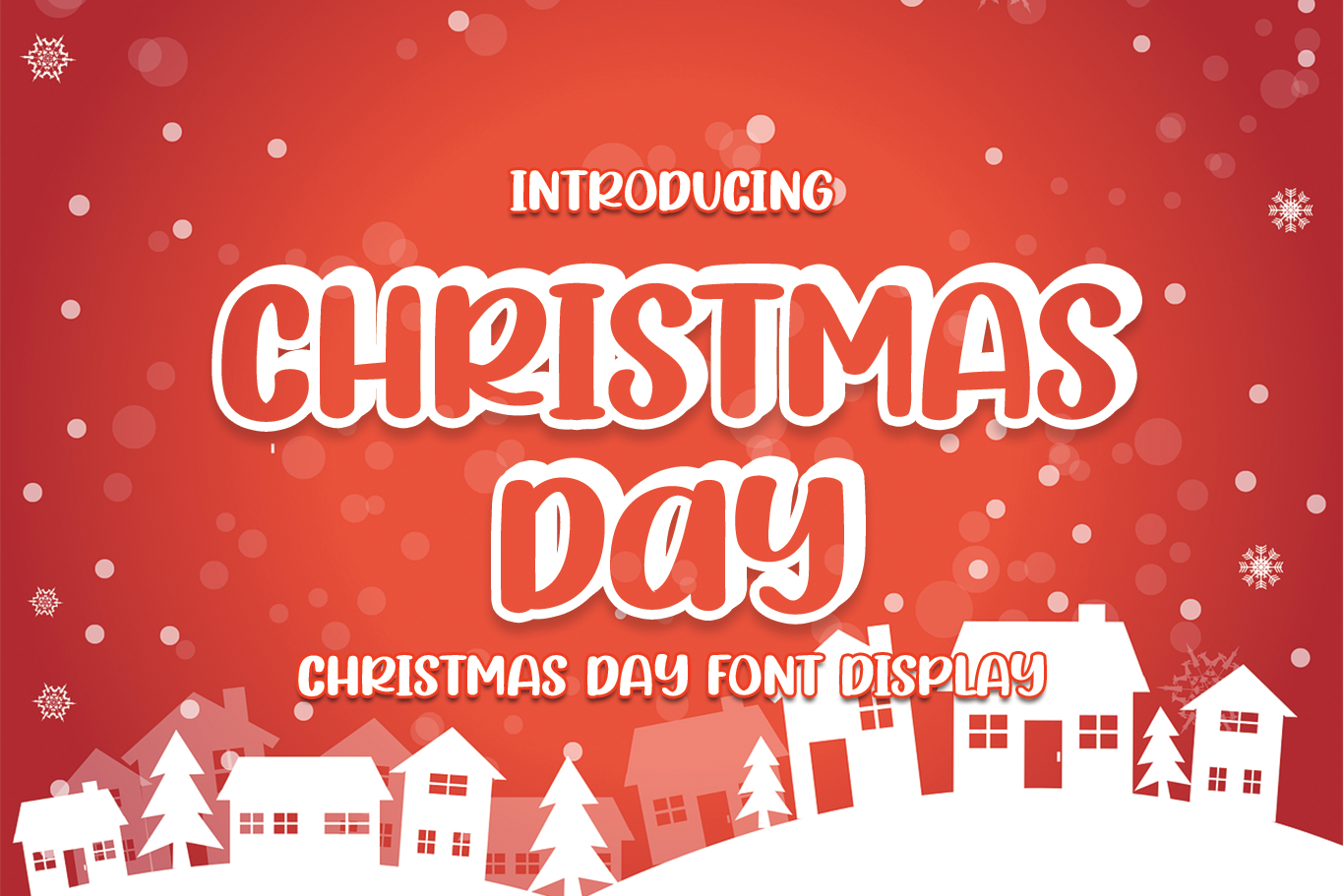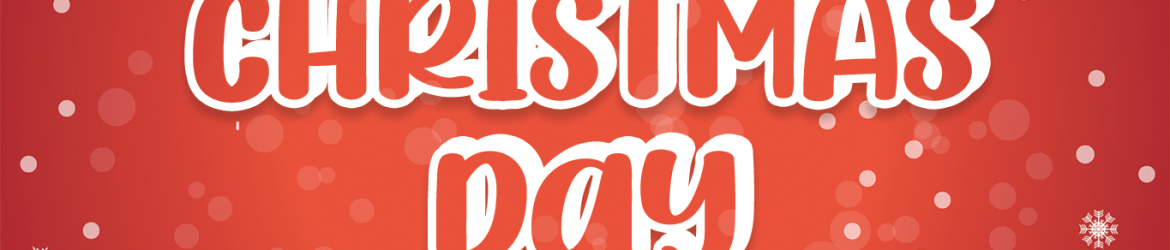
Christmas Day Font – Download Grátis
Esta é uma fantástica fonte de exibição para uso nos mais diversos projetos. Ela tem um ar descontraído e divertido que certamente trará vida ao seu design. Suas linhas retas e seus traços acentuados tornam a Christmas Day Font perfeita para ambientes onde você deseja destacar o texto, seja em cartões de aniversário, calendários ou até mesmo em tatuagens, sem falar dos famosos arquivos de emails de fim de ano. O designer Erik Studio criou uma fonte versátil e original que combina perfeitamente com sua personalidade criativa, tornando seus ideias ainda mais chamativas. Não espere mais para experimentar essa adorável fonte!